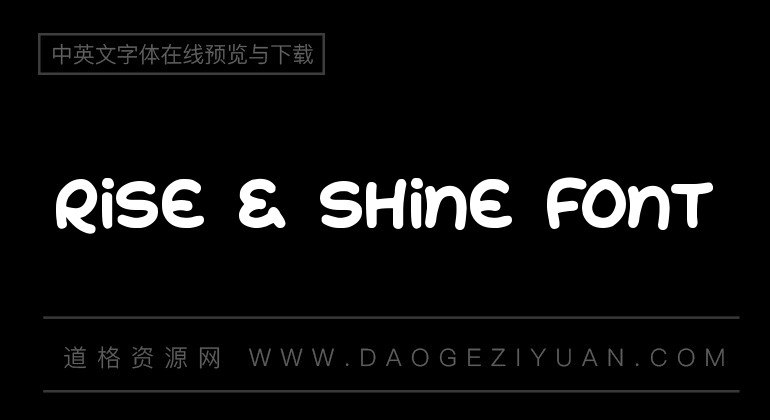
Rise & Shine Font 是一种非常流行的手写风格字体,它的设计灵感来自于手写字母和手绘艺术。这种字体具有明亮和欢快的外观,因此非常适合用于卡片、海报、广告、标志、标题和其他需要吸引人的设计项目。 Rise & Shine Font 设计师使用了一些有趣的设计元素来增强字体的个性和特点,例如在字母的形状和线条上添加了一些弯曲和变形,这使得 Rise & Shine Font 的每个字母都具有独特的外观。 此外,Rise & Shine Font 还包括一些特殊字符、数字和标点符号,因此您可以在您的设计项目中使用它来实现更丰富和独特的效果。总之,Rise & Shine Font 是一款非常适合用于创意设计和艺术作品的字体。内容介绍
Rise & Shine Font是一款非常不错的手写艺术字体,具有很好的视觉感,适合于文化类的宣传设计、商业类品牌的广告和产品包装设计以及个性化文字排版等较多场景。